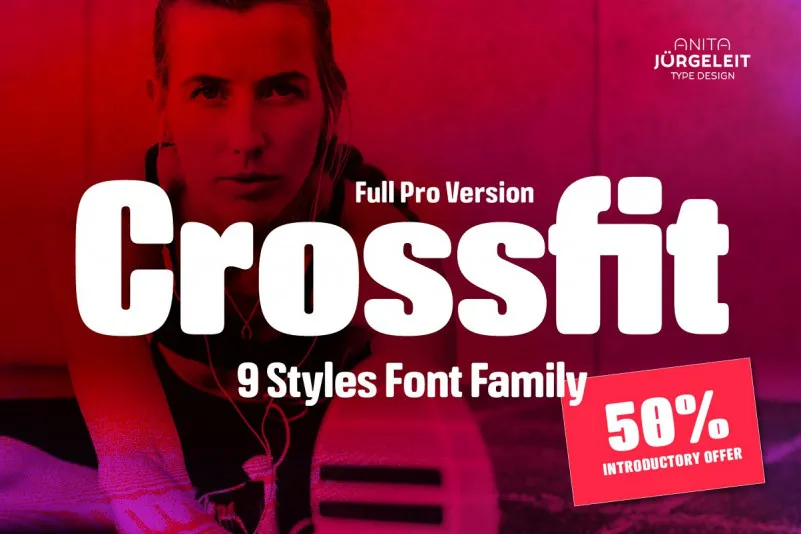
Esta é uma nova família de fontes sans-serif que inclui 9 estilos em 8 pesos. O tipo foi projetado para ser moderno, eficiente e confortável para uso em todas as aplicações. Introduzimos a Crossfit Font. Anita Jurgeleit desenvolveu e compartilhou este design. A família Crossfit é uma nova fonte de títulos adequada para grandes formatos, como posters de filmes, anúncios ou editoriais. Tem temas que podem ser aventura, esporte, natureza forte e todos os tipos de eventos-chave na vida. Suas estabilidade poderosa transforma seu trabalho em um design não contestável. É robusto, claro e também amigável devido às suas esquinas redondas. Com sua grande estabilidade sem excessos, a Crossfit destaca todas as suas criaturas incríveis no jornalismo, editoriais, design de títulos e, naturalmente: seus grandes blockbusters cinematográficos. A familia Crossfit Font é um excelente complemento para qualquer projeto visual que busque uma aparência moderna, clean e eficiente, sem esquecer dos detalhes essenciais da natureza do tipo humanoista. Seja você desenvolvedor de filmes, designer de gráfica ou editor editorial, a família Crossfit está aqui para ajudá-lo a destacar seu trabalho nos formatos que importam mais.